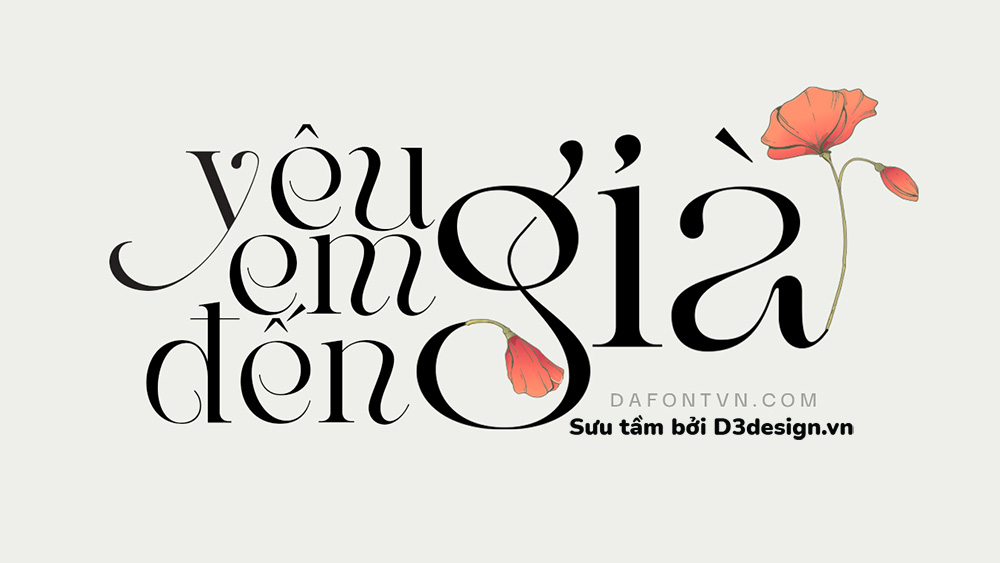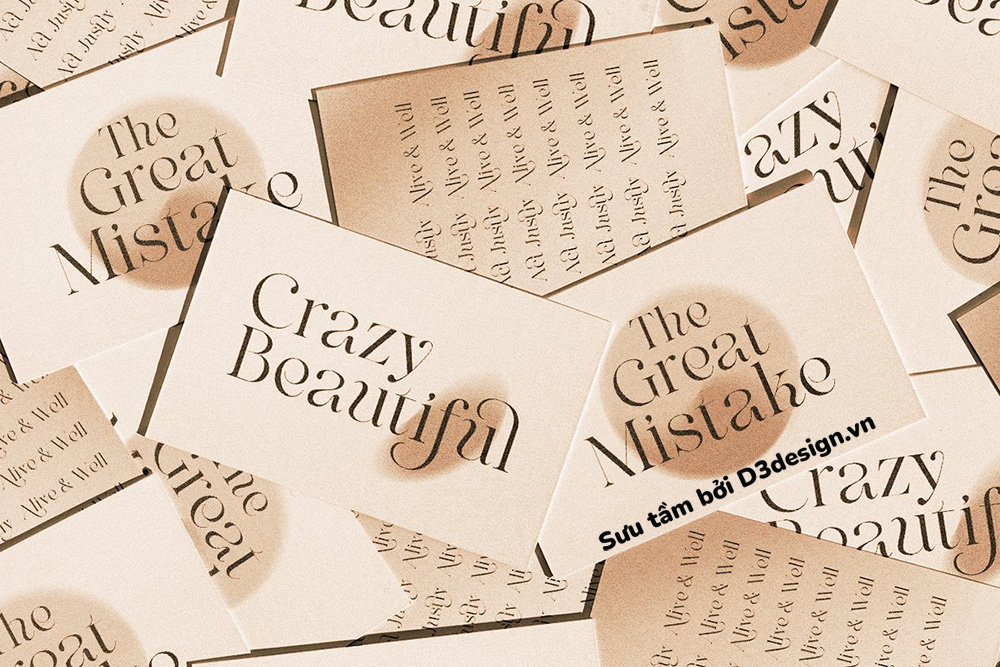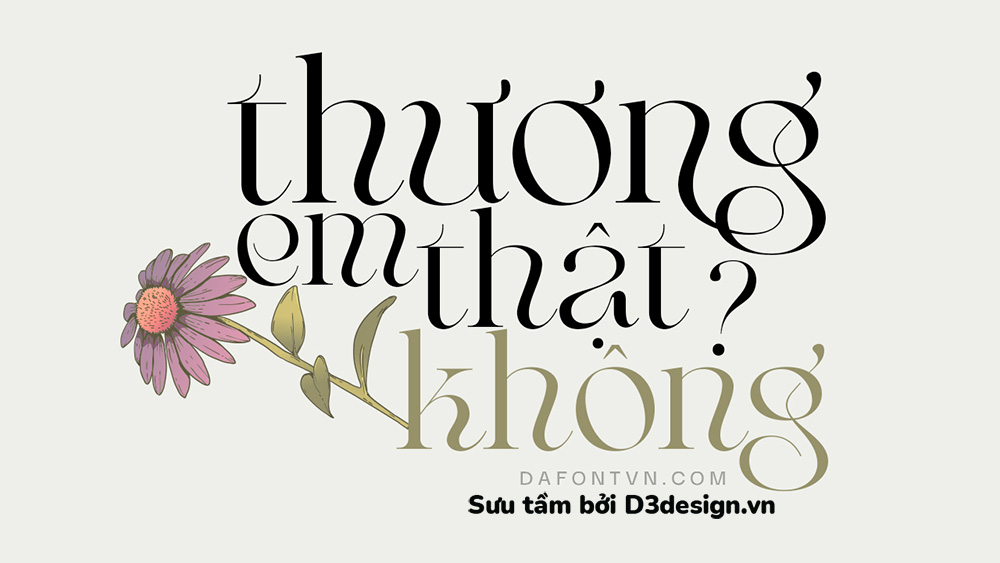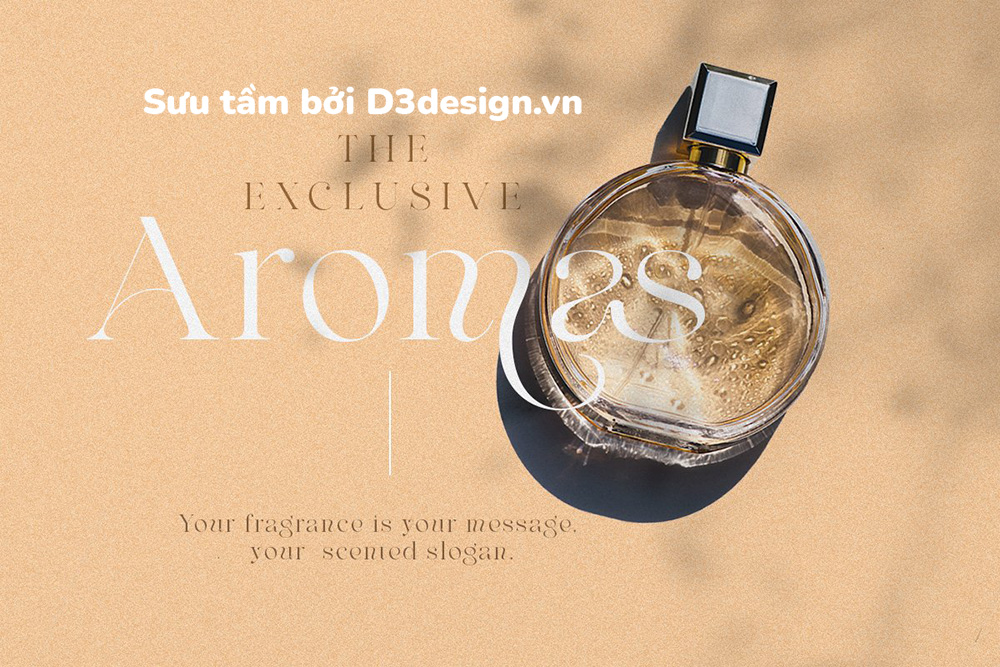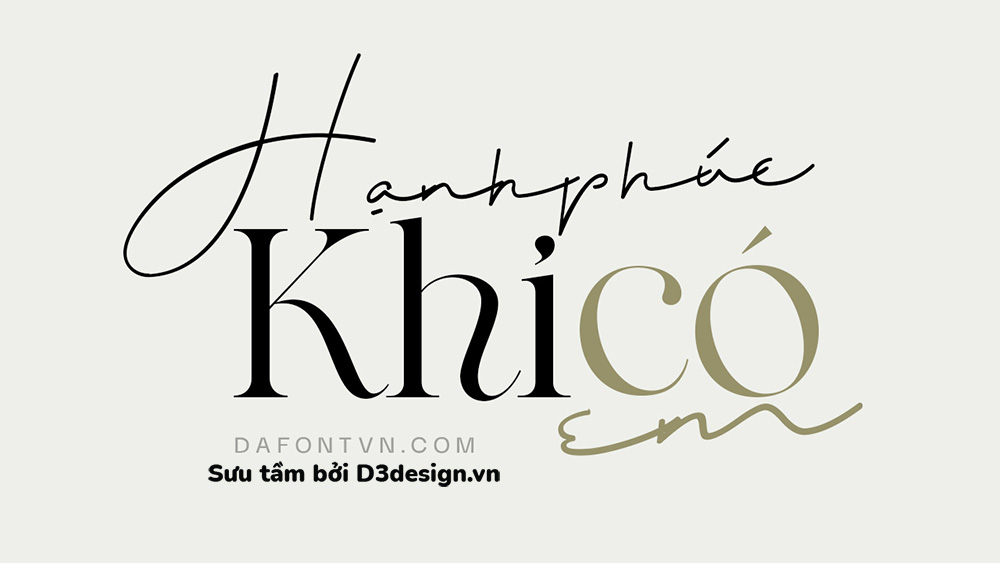
Font Việt Hóa - Maglite Mang Phong Cách Hiện Đại Và Mượt Mà
Font Maglite - Một kiểu serif đầy phong cách với các chữ ghép đẹp và các chữ xen kẽ uốn lượn! Maglite được thiết kế với các nét chữ hiện đại và mượt mà bạn có thể sử dụng nó cho nhiều thiết kế khác nhau như thiệp cưới, bao bì sản phẩm, bìa sách, typography, quotes... Ngoài ra font chữ đi kèm với các chữ ghép và xen kẽ được làm thủ công đẹp mắt làm cho phong chữ này trở nên phong cách và tuyệt vời hơn.
Font Maglite việt hóa đầy, kerning lại, chỉnh sửa cũng như tối ưu, bạn nên sử dụng phần mềm Illustrator để có tận dụng được tất cả các glyph cực đẹp của font này nhé.